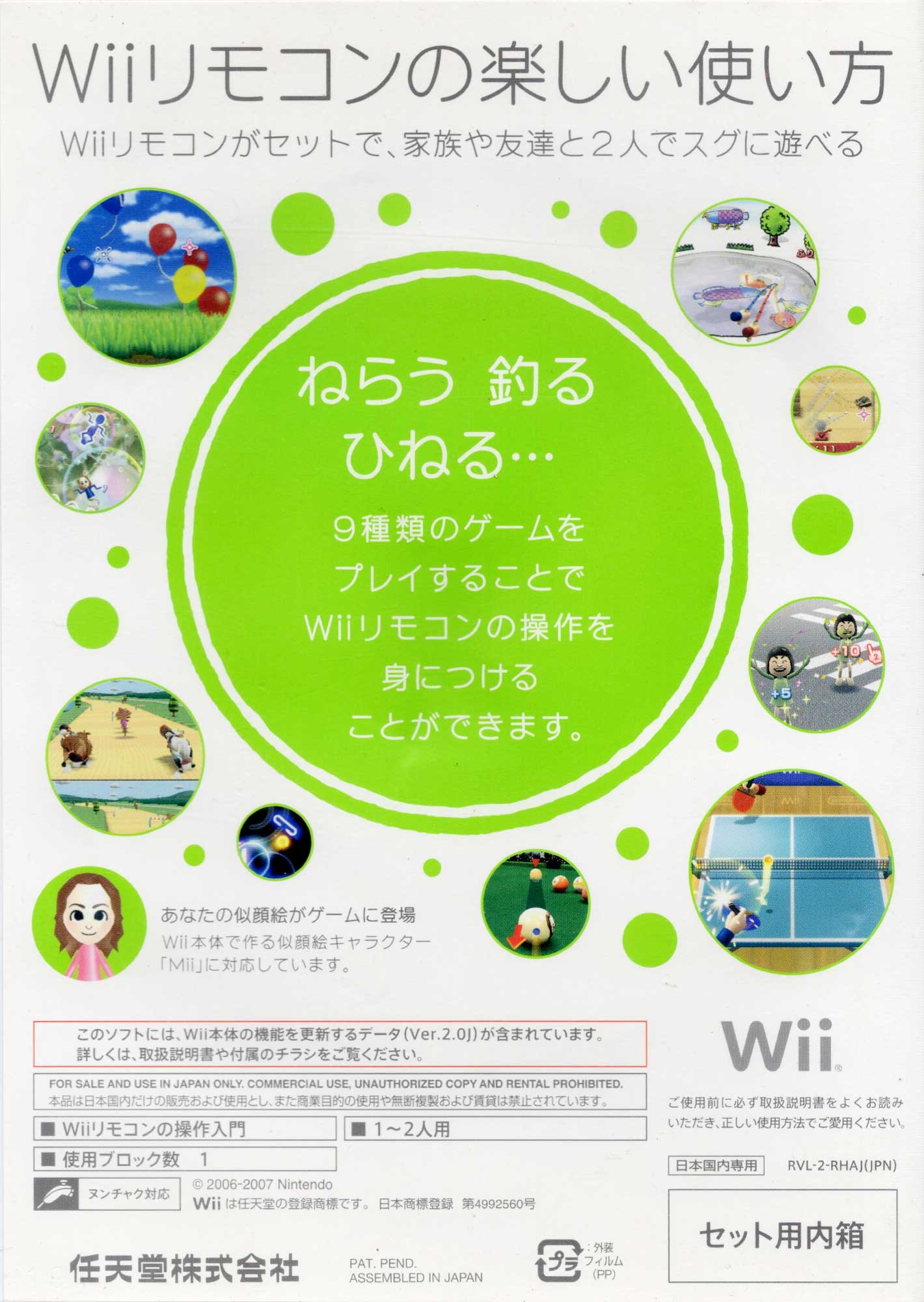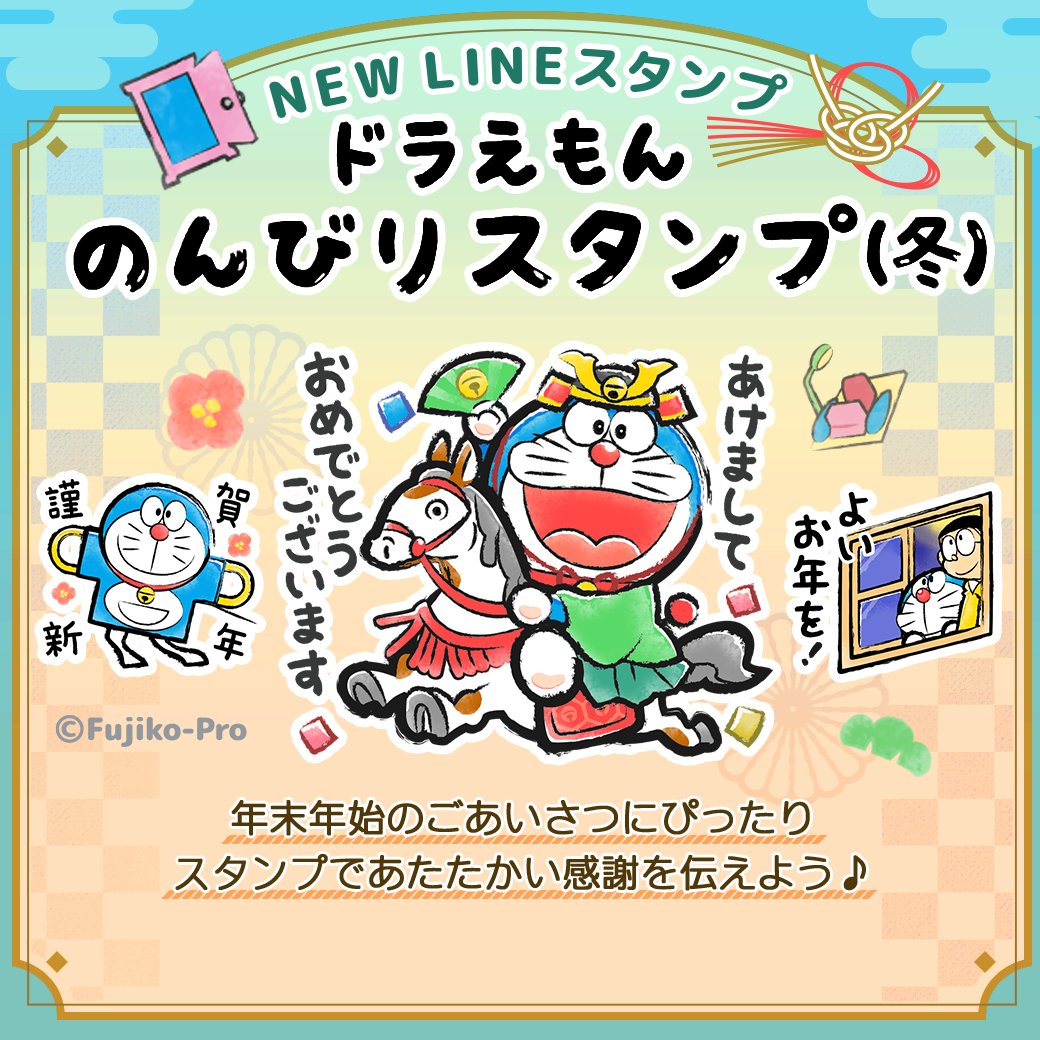
タイプラボが頒布している「アニト」だけでなく
アニト書体はフォントワークスやニィスからも販売されています
ドラえもんチャンネルの公式Xに投稿されていた販促画像でアニトが使われていました。
「年末年始の〜伝えよう♪」のところですね。
他社にライセンスされてるものと「た」のデザインが違うので、タイプラボで頒布されているアニト…ではないかと思います。
あまり目立たない書体なので、使用例はありがたいです。
Wiiソフト「はじめてのWii」(2006年発売)のパッケージ裏のデザイン。
大きいサイズで「アニト」が使われています。
ひさしぶりにアニト書体を見ました。
きれいにデザインされていて、逆に目立たないんですよね…。
放送中のTVアニメ「結婚するって、本当ですか」の劇中で(メッセージアプリの文字に)使われていたアニトです。
画像は同アニメの第2話より。
これも。
劇中のスマホ画面のフォントまでチェックしてくれて、ありがとう!!!!
書名:竹達彩奈 写真集「あやちさん in ITALY」
発行:ポニーキャニオン
「あやちさん in ITALY」の文字がアニト書体のようですね。
瀬戸弘司というYouTuberの動画内で「アニト」を見つけました。
なかなか大きくキレイに使われています。
これも。
最後にこれも。
英数字の天地が、漢字やかな文字と同じなので、使いやすいと思います。
2018年に放送されたTVアニメ「宇宙(そら)よりも遠い場所」のPV(1・2弾)のテロップでアニトが使われています。
「4人の少女が〜グラフィティ」のところですね。
これも。
最後にもう1枚。
地味だけど、いい書体ですよね。
アイフルのテレビCM「凛とした女将」シリーズの第11弾です。
右下の「生」と「配信中」の文字が「アニトインライン」のようです。
「生」の部分は文字色を背景と同じ色に、「配信中」の部分はハート型の図形と同じ色に指定して使っているんだと思います。
演出上、映像が暗かったので画像は少し明るくしました。
よく気づいてくれました〜。
放送中のアニメ「よふかしのうた」の劇中で使われていた「アニト」です。
青いバックの上の白い文字ですね。
有料放送って、私はほとんど見たことがありません…。
「関ジャム∞完全燃SHOW」のテロップでアニトが使われていました。
これも。
(右下の「キンプリ〜」のところ)